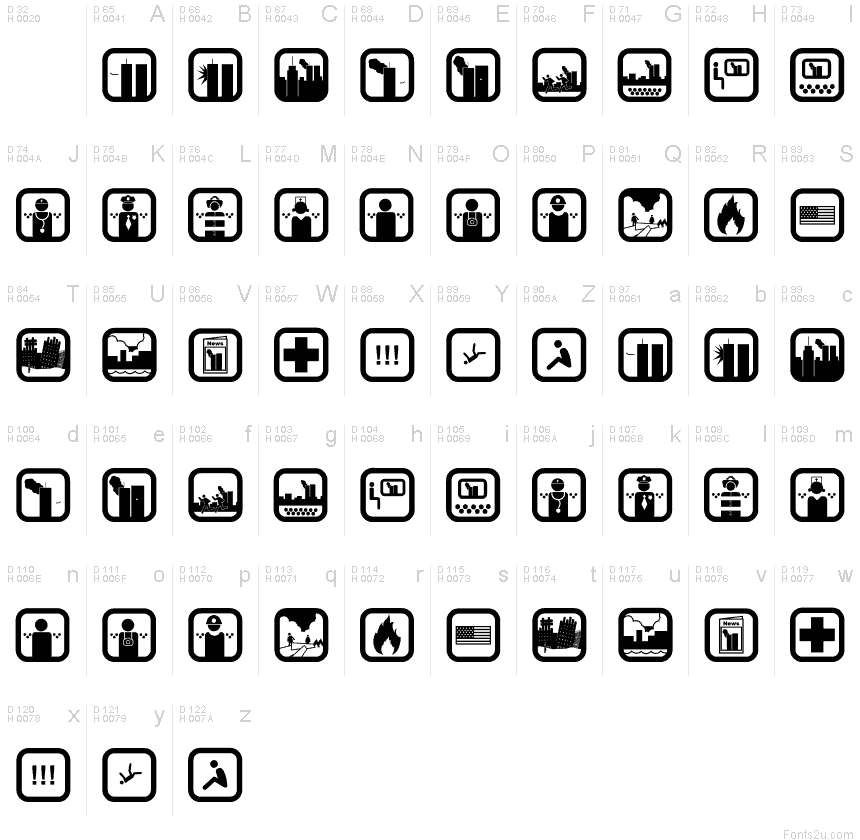
SEPTEMBER 11 ICON
" september 11 icon "
esta iconografia pasa a dingbat
fue con la idea o el concepto de
representar algo que haya impactado al mundo de una forma
simple y concreta como son los
iconos.